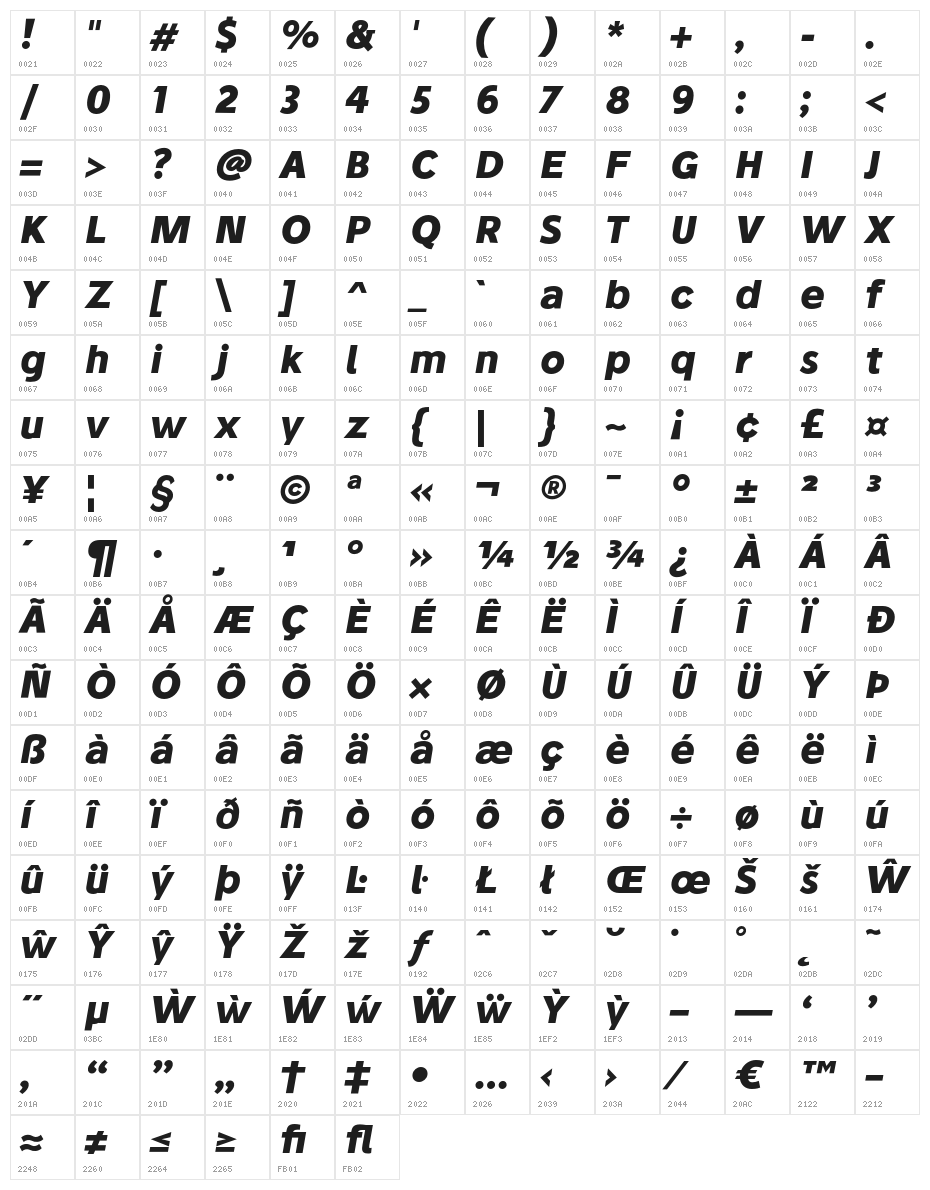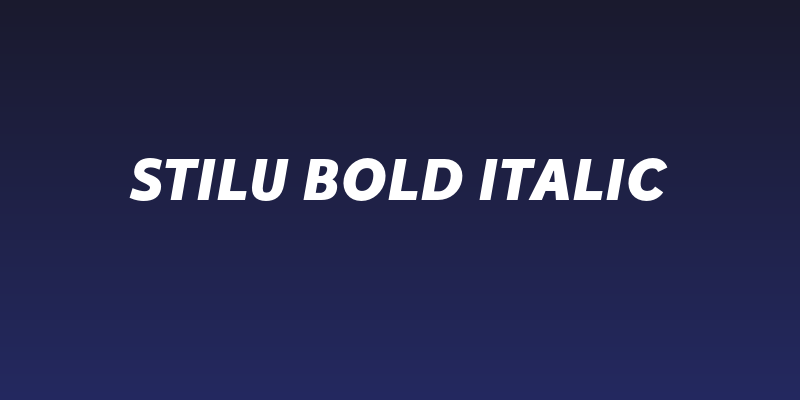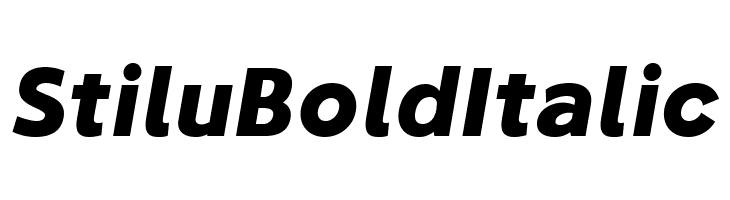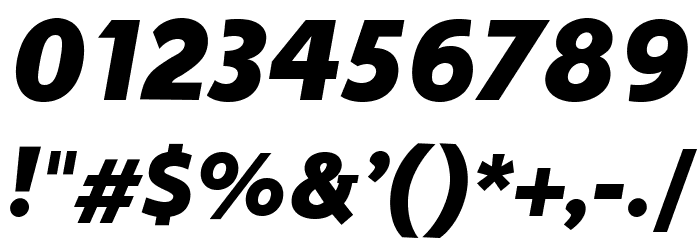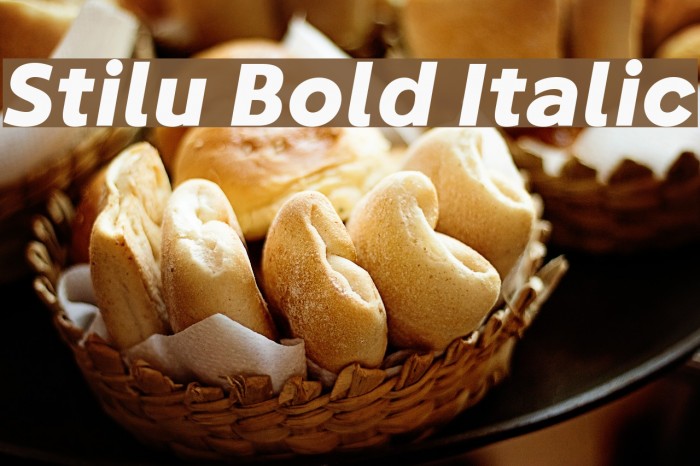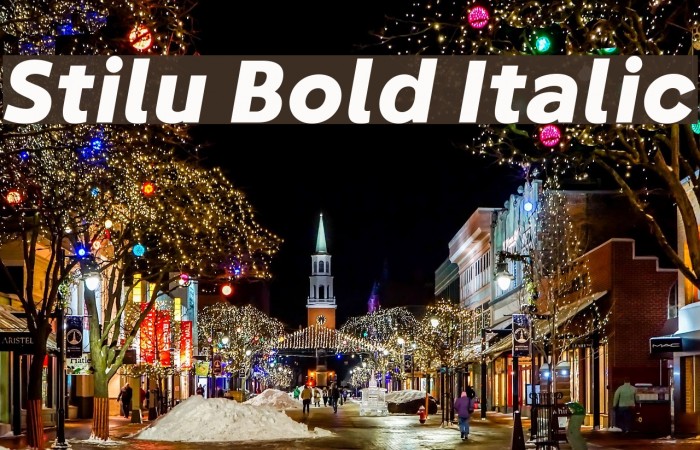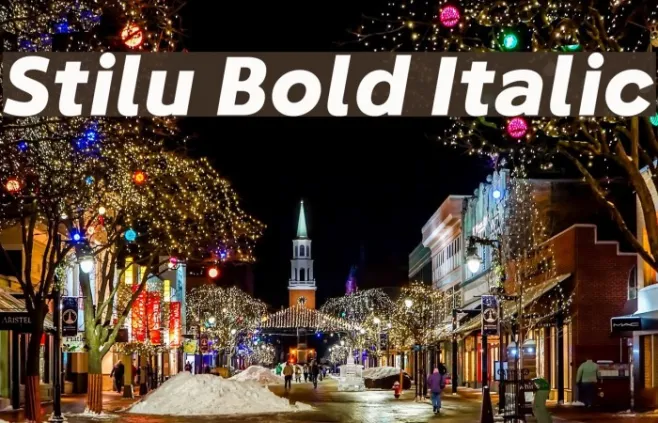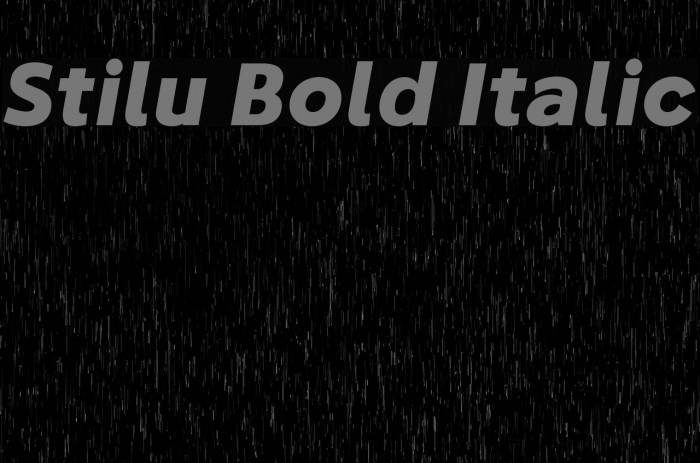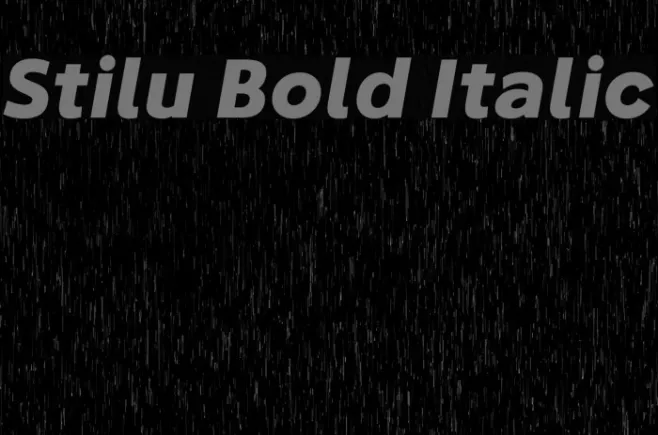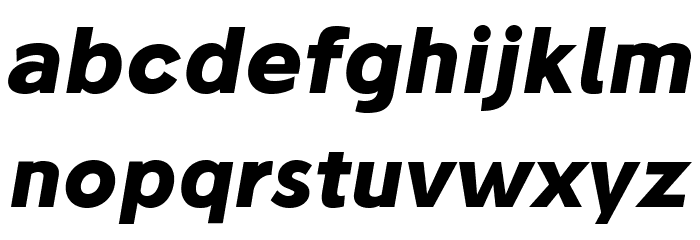
Stilu Bold Italic Font
| Vorgeschlagene Projekte | Ideal for branding, advertising, headlines, and posters where a strong and modern impression is needed. |